Polices gratuites | Où les trouver ?
Créer son CV, un diaporama, une affiche publicitaire, ou même un logo pour sa marque requiert d’utiliser une ou plusieurs polices de caractères. À partir du moment où l’on insère du texte dans son visuel, difficile d’y couper…
Or, décider d’employer une police d’écriture plutôt qu’une autre n’est jamais un acte anodin. Ce choix influence immédiatement la façon dont le public perçoit votre message, ainsi que sa lisibilité.
En la matière, on entend souvent qu’il est indispensable de se tourner vers des ressources payantes (et volontiers onéreuses), car les polices gratuites ne « feraient pas le job ». Et pourtant…
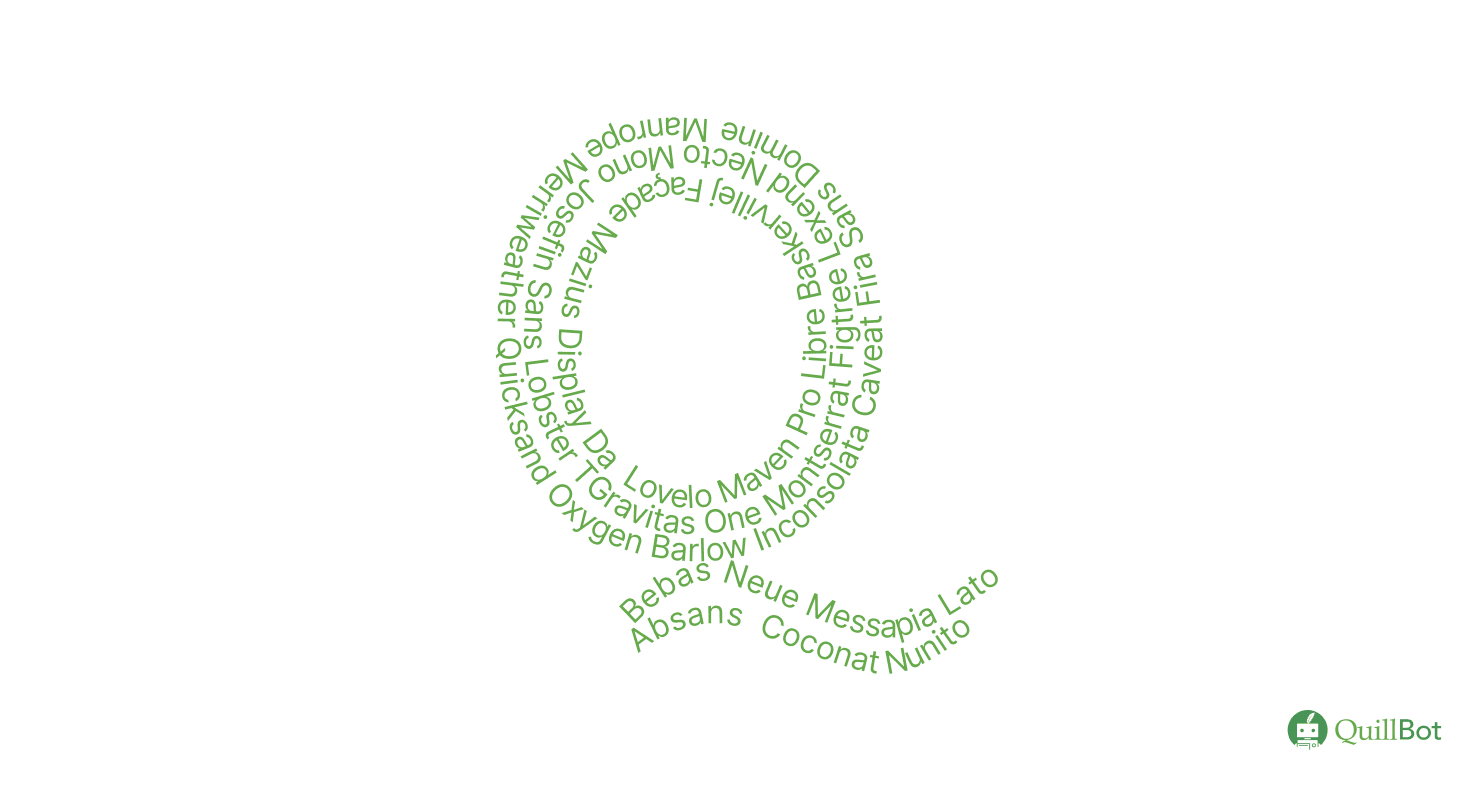
En vérité, le web regorge d’excellentes polices gratuites et complètes, qui ne demandent qu’à faire briller vos projets.
Mais attention : pour bien les utiliser, il faut respecter quelques bonnes pratiques de recherche et s’assurer de cocher un certain nombre de paramètres pour éviter les mauvaises surprises à l’impression… voire sur le plan juridique.
Trouver des polices d’écriture gratuites
Sur Internet, en matière de polices d’écriture gratuites, il existe des centaines de milliers de ressources référencées par les moteurs de recherche. Toutefois, séparer le bon grain de l’ivraie s’avère indispensable si l’on ne veut pas se retrouver avec des fichiers défectueux au mieux, infectés par des virus au pire dans son ordinateur…
Pour ce faire, se fier à une liste peut sembler un bon début.
Entre bons plans méconnus et grands classiques qui font désormais autorité, suivez le guide !
Liste des meilleurs sites pour télécharger des polices d’écriture gratuites
- Google Fonts : Il est le premier réflexe de nombreux graphistes du dimanche en la matière, et même de certains pros qui ne l’assument pas toujours… Le géant Google met à disposition de ses utilisateurs un catalogue de polices large, facile d’accès et pratique à utiliser. Il y en a pour tous les goûts, toutes ses références sont sous licence open source (soit gratuites et modifiables). Vous pouvez y aller les yeux fermés ! Mention spéciale pour son outil de prévisualisation, ou bien au fait que l’on peut directement saisir le code HTML de la police pour l’intégrer à un site web.
- DaFont : Connu pour ses catégories variées et parfois fantaisistes, lesquelles proposent des polices originales, l’agrégateur de polices DaFont est un emblème du genre. Le site propose aussi des modèles classiques dans une section dite « Basique ». En clair, c’est la caverne d’Ali Baba. Attention : la plupart des polices suggérées sont gratuites pour un usage personnel, mais non plus si l’on souhaite les employer à des fins commerciales. On compte également quelques références entièrement gratuites (tout comme d’autres sont strictement payantes), mais elles sont minoritaires. Heureusement, les mentions légales sont clairement affichées.
- FontSpace : FontSpace se targue de répertorier plus de 160 000 polices gratuites sur son site. La plupart le sont pour un usage personnel uniquement, mais quelques-unes se démarquent en arborant la mention « 100 % Free ».
- FontShare : Outsider de cette liste, FontShare est un site indien à la présentation ultra-moderne, qui propose de nombreuses polices gratuites et uniques — vous ne les trouverez nulle part ailleurs. Il est clairement mentionné à propos des licences que « 100 % des polices proposées par FontShare sont gratuites pour un usage personnel ET un usage commercial ». Certaines typographies sont open source (donc modifiables), d’autres non. À vous d’ajuster vos recherches en conséquence, mais les modalités d’utilisation sont clairement indiquées à chaque fois.
- UrbanFonts : Construit dans le même esprit que DaFont, avec toutefois un design plus épuré, UrbanFonts annonce clairement la couleur avec un onglet « Free fonts » dans le menu supérieur de la page d’accueil. Impossible de vous tromper !
- Velvetyne : Amateur(trice) de polices iconoclastes, Velvetyne est fait pour vous ! Ce catalogue de polices 100 % open source, tant pour un usage personnel que commercial (ce qui signifie que vous pouvez les retoucher à loisir selon votre goût et vos besoins), a été pensé pour servir les usages artistiques et publicitaires avant tout, mais il recèle des bijoux pour chaque profil.
- Awwwards : Prisé des web designers, Awwwards n’est pas un agrégateur de polices à proprement dit, mais il propose, dans un onglet dédié, des liens avec plusieurs polices de caractères singulières, à l’identité assumée, pour l’immense majorité d’entre elles disponibles en open source.
- Abstract Fonts : Parmi les polices disponibles sur Abstract Fonts, vous trouverez des typographies gratuites, parfois seulement pour un usage personnel, mais d’autres fois pour un usage commercial également. Avis aux explorateurs !
- Ma police présente-t-elle toutes les graisses (gras, italique…) requises pour mon usage ?
- Est-ce que les crénages et les espacements sont ajustés pour une lisibilité optimale ?
- Ma police est-elle aussi bien lisible sur écran que sur papier, et dans toutes les tailles ?
- La police que j’ai choisie correspond-elle à l’esprit de ma marque et à ce que je projette d’en faire sur le long terme, et pas uniquement à mon goût personnel ou mon impulsion du moment ?